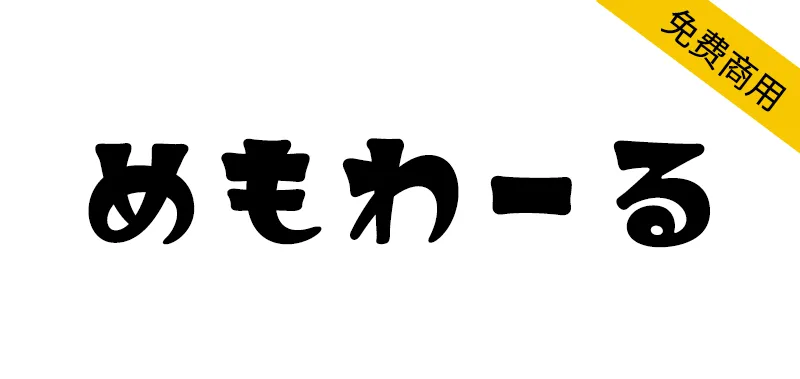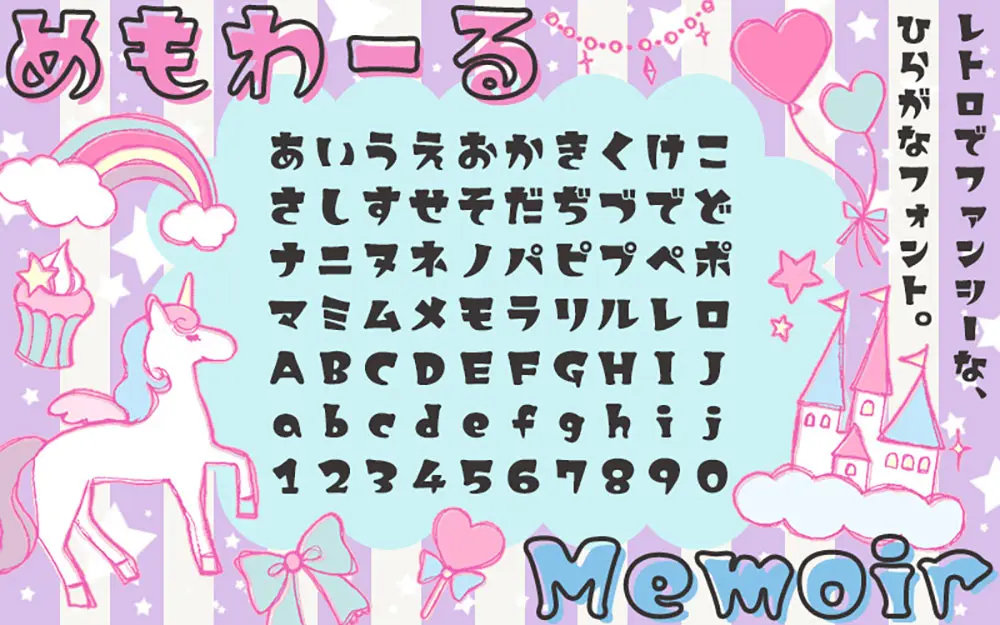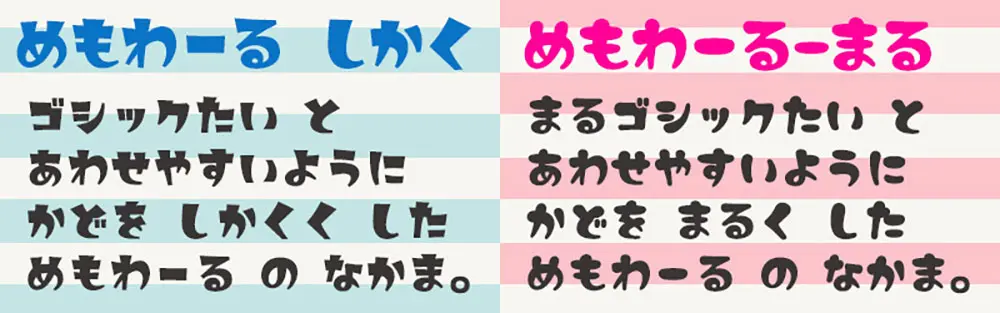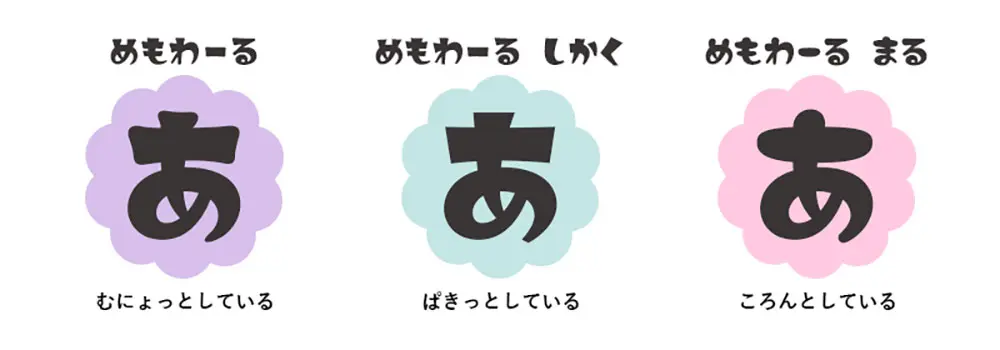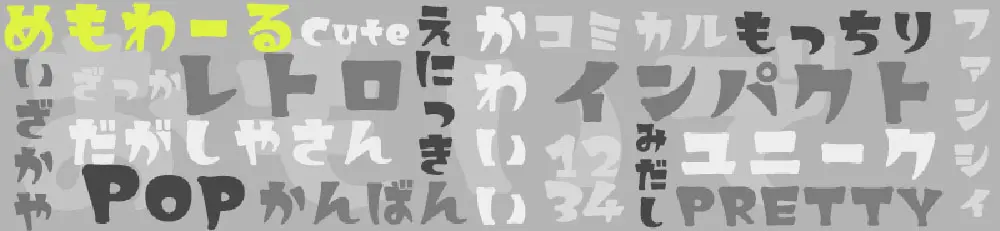
めもわーる(Memoir)這是一種以精美雜貨為形象而創作的具有影響力的復古流行平假名字體。
但它似乎也適合像“hoppy”這樣的詞。
Memoir是一個法語單詞,意思是記憶。
平假名、片假名、字母數字字符。
此外,還包括一些基本的標點符號(標點符號、括號等符號)。
ファンシー雑貨のイメージで作った、インパクトのあるレトロポップなひらがなフォントです。
でも「ホッピー」とかの単語にも似合いそう。
Memoir(メモワール)はフランス語で記憶や思い出のこと。
ひらがな・カタカナ・英數字。
おまけでいくつか基本的な約物(句読點や括弧などの記號)も入っています。